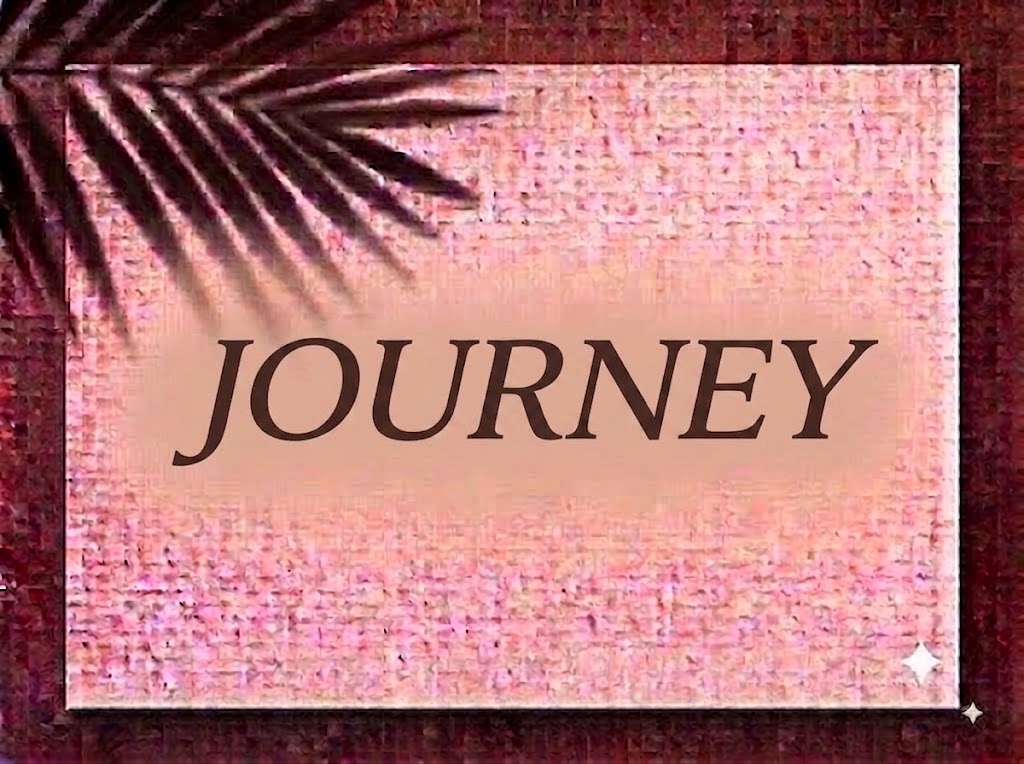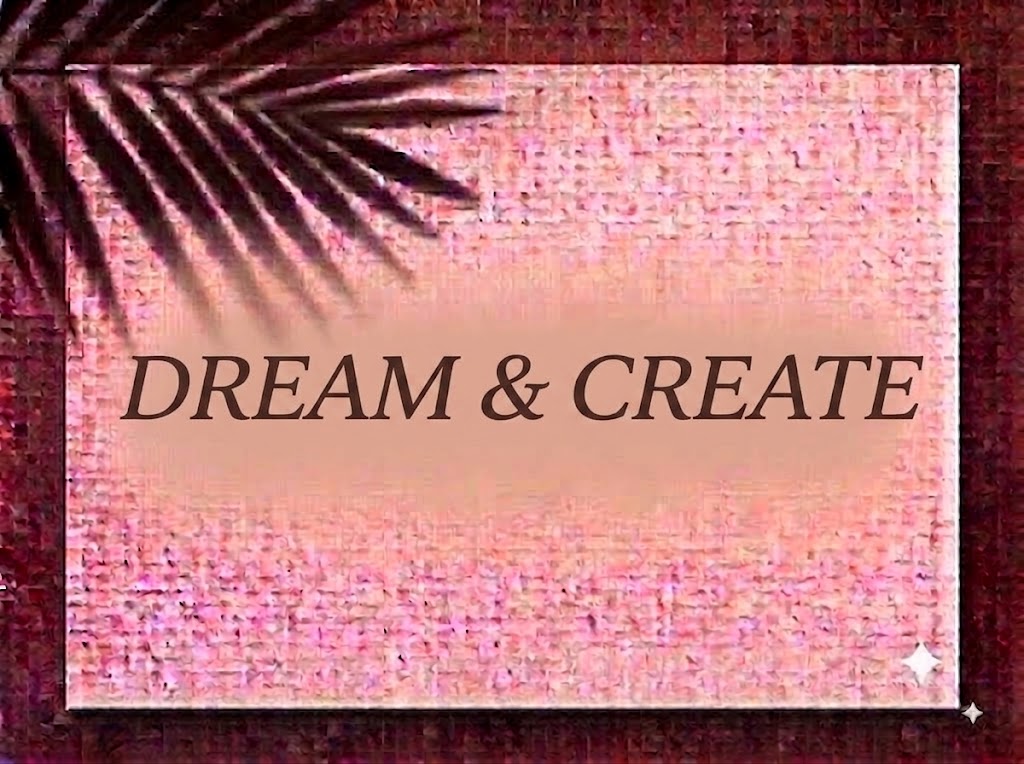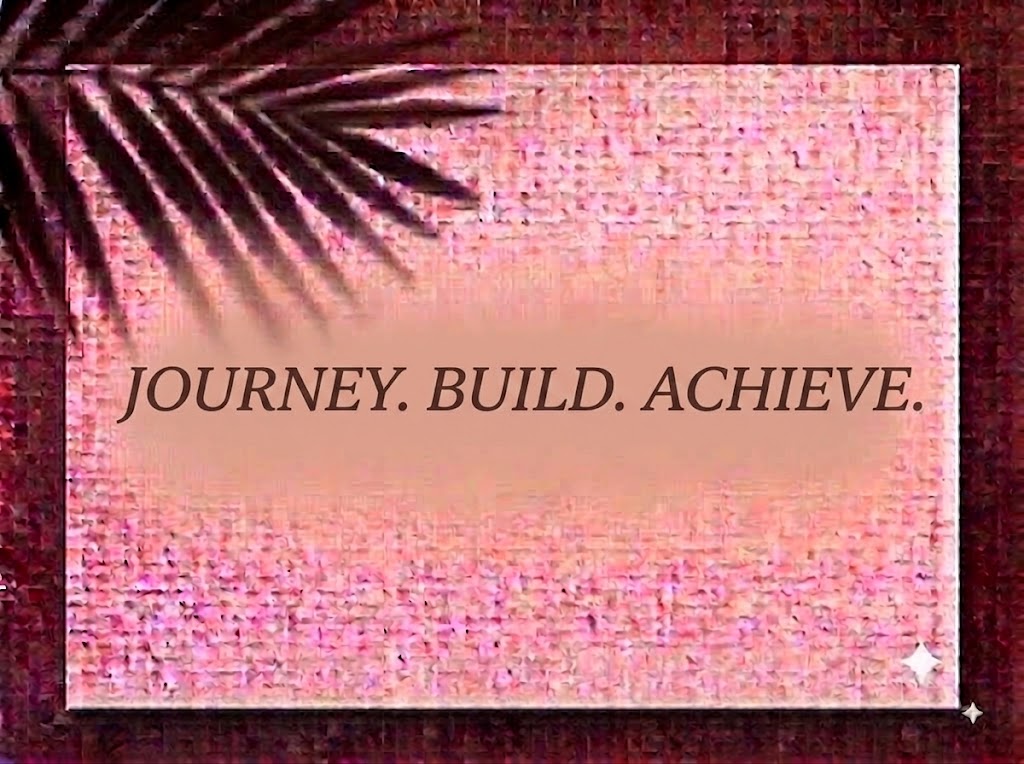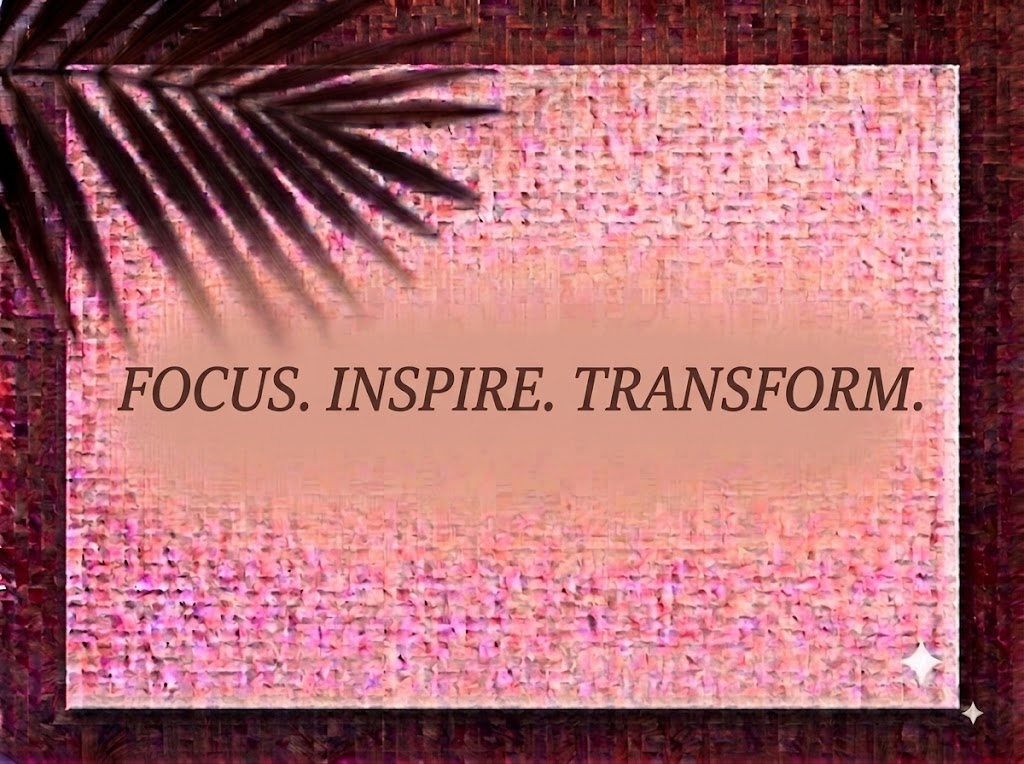
1FTV VIP Bregan Ita
Trong nghệ thuật thiết kế đồ họa thị giác và truyền thông đa phương tiện, các biến thể chữ không chân hình học dáng nghiêng (Geometric Sans-Serif Italic) luôn mang đến nguồn năng lượng bứt phá. Độ nghiêng chuẩn xác kết hợp cùng các đường cong hình học mở rộng không chỉ tạo cảm giác chuyển động, tốc độ và tính công nghệ vượt trội mà còn giúp các tiêu đề chính nổi bật dứt khoát trên khung hình.
Nếu bạn đang tìm kiếm một phông chữ không chân dáng nghiêng thời thượng, tinh gọn để làm nhận diện thương hiệu công nghệ, thể thao, thiết kế giao diện (UI/UX) hay giật tít video ngắn triệu view, font 1FTV VIP Bregan Ita chính là mảnh ghép không thể bỏ qua.
Giới thiệu về font 1FTV VIP Bregan Ita
Font 1FTV VIP Bregan Ita là phiên bản in nghiêng (Italic/Oblique) của dòng chữ Bregan danh tiếng, mang phong cách Geometric Sans hiện đại với cấu trúc khung hình học chuẩn mực:
Tên phông chữ: 1FTV VIP Bregan Ita
Đặc điểm nổi bật của ngôn ngữ thiết kế VIP Bregan Ita
Sức hút thị giác của font 1FTV VIP Bregan Ita đến từ sự giao thoa hài hòa giữa cấu trúc hình học tròn trịa và góc nghiêng tràn đầy tính chuyển động:
Góc nghiêng mang tinh thần tốc độ (Dynamic Italic): Thân chữ nghiêng đều về phía trước tạo cảm giác chuyển động linh hoạt, hướng tới tương lai. Đây là phong cách rất được ưa chuộng trong các thiết kế liên quan đến thể thao, xe cộ, gaming và công nghệ đột phá.
Cấu trúc hình học mở rộng (Extended Geometric): Các ký tự như
o,e,c,a,d,b,ggiữ nguyên phom dáng bo tròn đầy đặn của họ Bregan, tạo độ thoáng đãng cho bố cục tiêu đề. -
Độ dày nét đồng đều (Monoline): Tỷ lệ tương phản cực thấp giữa các nét giúp từng con chữ hiển thị sắc cạnh, mạch lạc ngay cả khi đặt trên các phông nền video chuyển động liên tục.
Tối ưu hiển thị và dấu tiếng Việt từ 1FTV
Để phông chữ vận hành hoàn hảo trên cả nền tảng Windows và macOS, phiên bản này đã được xử lý kỹ lưỡng về mặt thông số nội tại:
Khoảng cách ký tự (Kerning): Khoảng hở giữa các chữ nghiêng được tinh chỉnh tỉ mỉ, đảm bảo các nét gạch chéo không bị chạm hay đè lên nhau.
Bản Việt hóa chuẩn chỉnh: Hệ thống dấu tiếng Việt (sắc, huyền, hỏi, ngã, nặng, mũ, móc) từ fonttiengviet.com được tạo góc nghiêng đồng điệu 100% với thân chữ, đặt đúng trọng tâm thị giác giúp tổng thể từ ngữ liền mạch và thẩm mỹ.
Hệ thống ký tự đồng bộ: Tích hợp trọn vẹn bộ chữ in hoa, in thường, dãy số 0-9 cùng đầy đủ các ký hiệu toán học và dấu câu cơ bản.
Đánh giá hiển thị thực tế
Khả năng hiển thị của phông chữ được tối ưu linh hoạt theo nhiều kích cỡ:
Kích thước nhỏ (12pt – 24pt): Nhờ cấu trúc nét đơn tuyến rõ ràng, các dòng text tiếng Việt và chữ số vẫn giữ được độ rành mạch, dễ đọc trên giao diện ứng dụng điện thoại.
Kích thước lớn (36pt – 72pt): Đây là đất diễn lý tưởng nhất để 1FTV VIP Bregan Ita phô diễn toàn bộ sự khỏe khoắn, hiện đại và nhịp điệu tốc độ cho các dòng headline chính và ảnh thumbnail.
Ứng dụng trong thiết kế đồ họa và sản xuất video
Sở hữu nét cá tính hiện đại và năng động, font 1FTV VIP Bregan Ita mở ra không gian ứng dụng phong phú:
Video ngắn (TikTok, Reels, Shorts): Dáng chữ nghiêng hiển thị rất hút mắt trên khung hình đứng tỷ lệ 9:16. Cực kỳ ăn nhập với các video review đồ công nghệ, tin tức xe cộ, workout/fitness, gaming highlight hay vlog du lịch khám phá.
Ảnh thu nhỏ YouTube (Thumbnail): Vũ khí giật tít hiệu quả cho các kênh Tech review, AI, xe thể thao, tài chính hoặc gaming nhờ khả năng tạo điểm nhấn thị giác thôi thúc người xem nhấp chuột.
Nhận diện thương hiệu Tech & Sport: Hoàn hảo để thiết kế logo dạng chữ, banner website, catalog sản phẩm cho các công ty công nghệ, studio game, nhãn hàng thời trang thể thao hay thiết bị số.
Poster Sự kiện & Banner Quảng cáo: Thích hợp cho các ấn phẩm truyền thông sự kiện công nghệ, giải đấu thể thao, chương trình âm nhạc điện tử và banner flash sale.